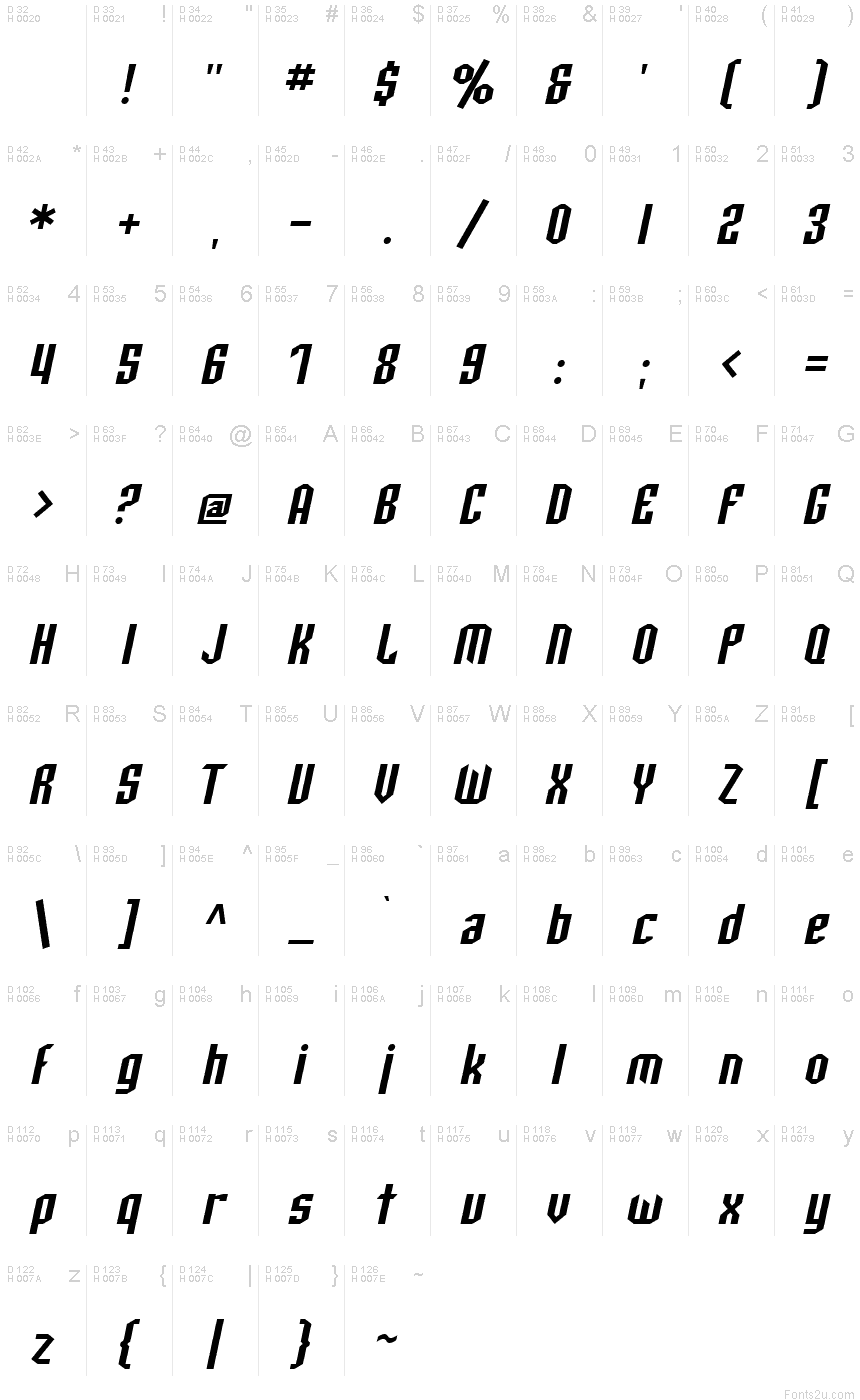
SF Archery Black Oblique
SF Archery Black Oblique od ShyFonts Type Foundry je bezplatné hranaté techno písmo typu display s agresivním náklonem a dynamickým charakterem. Písmena vypadají jako vysekaná z ostrých bloků, se strmými diagonálami, zkosenými rohy a těsnými spoji, které ho posouvají spíše k atmosféře herních automatů z konce 90. let a sportovních technologií než k neutrálnímu futurismu.
Hodí se na plakáty, branding her, letáky, loga či obaly alb a mixtapeů, kde krátká slova potřebují ten správný dravý švih. Protože jde o bezplatné písmo, využijete ho i na titulní karty, jména ve stylu dresů a úzké nadpisy – husté tvary a ostré řezy dodávají i krátkým slovům pocit pohybu.